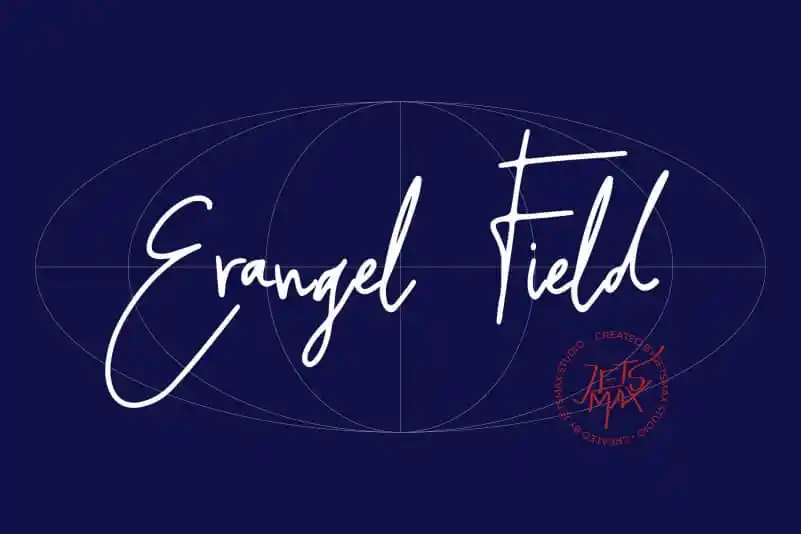
Erangel Field Handwritten Font – Download Grátis
A Erangel Field Handwritten Font é uma escolha perfeita para quem busca dar vida ao seu design com um estilo autêntico e naturalmente realista. Se você está procurando por um elemento que dê aos seus projetos uma aparência cuidadosamente feita à mão, esta fonte será sua melhor aposta. Ela traz a característica única dos textos escritos com as próprias mãos, oferecendo um toque de autenticidade e habilidades de designer artesanal que se destacam em qualquer projeto visual. A Erangel Field é o recurso ideal para aqueles buscando transpor sua personalização e estilo através de uma fonte elegante e naturalmente handwritten.